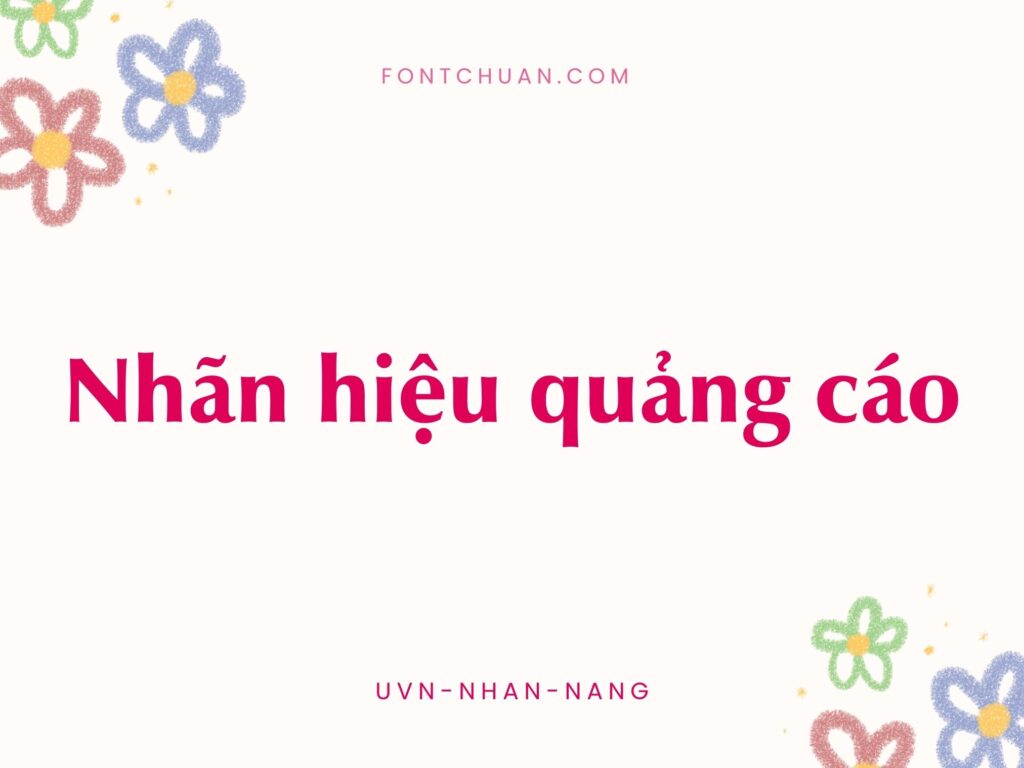
Font UVN Nhan Nang Việt Hóa
UVN Nhàn Nặng là phiên bản đậm hơn của bộ font UVN Nhàn, mang phong cách hiện đại kết hợp nét mềm mại truyền thống, phù hợp cho các thiết kế cần tạo điểm nhấn mạnh mẽ. Với sự tròn trịa và chắc chắn trong từng ký tự, font thể hiện sự vững vàng, giúp làm nổi bật tiêu đề hoặc thông điệp chính trong thiết kế. Font này chỉ được sưu tầm và đăng bởi thành viên của Font Chuẩn nhằm phục vụ cộng đồng thiết kế Việt, mang lại lựa chọn đa dạng cho các dự án in ấn và số hóa.
Thiết kế của UVN Nhàn Nặng nổi bật với độ dày đều, các đường nét uyển chuyển vừa đủ để tạo sự cân bằng giữa thẩm mỹ và khả năng đọc. Font không có nhiều ligatures nhưng giữ cấu trúc ổn định, dễ căn chỉnh. Phù hợp để sử dụng cho poster, tiêu đề tạp chí, biển quảng cáo hoặc nhận diện thương hiệu. Các ngành nghề như quảng cáo, bất động sản, giáo dục, công nghệ, và ẩm thực có thể tận dụng font này hiệu quả. Đồng thời, font cũng phù hợp với các sự kiện như Tết, lễ hội, sinh nhật hoặc ngày nhà giáo.